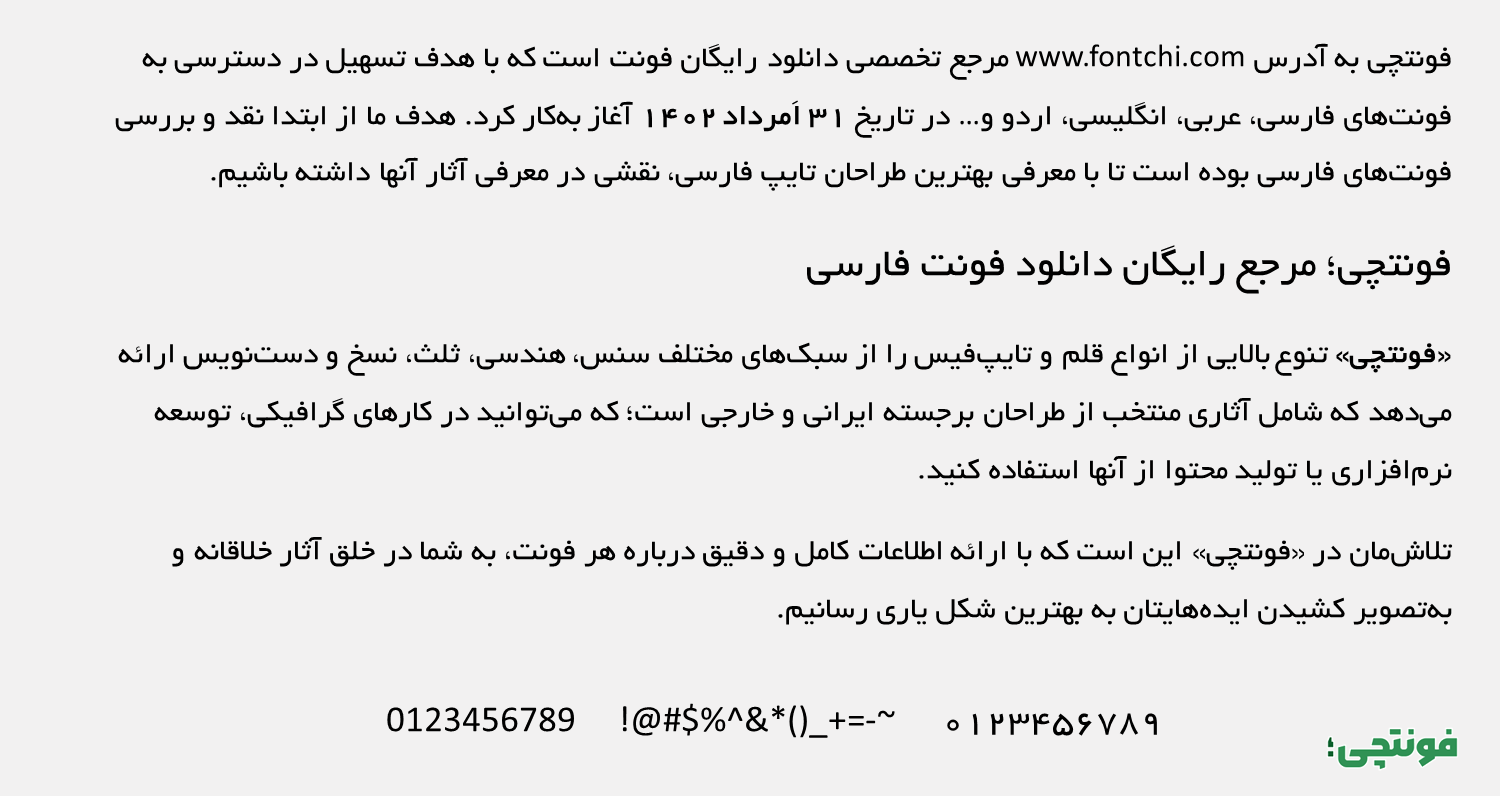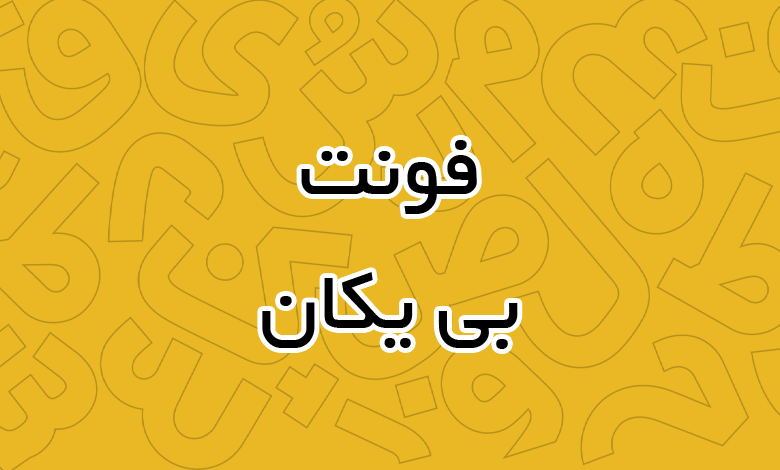
فونت بی یکان (B Yekan)
فونت بی یکان (به انگلیسی: B Yekan) جزو اولین فونتهای فارسی است که بیش از دو دهه از انتشار آن میگذرد. این فونت فارسی دارای یک وزن معمولی است که امکان بولد کردن متون را نیز به شما خواهد داد و بر خلاف سایر فونتهای حرفهای خبری از وزنهای متنوع نیست.
پیشنمایش و امکانات فونت بی یکان (B yekan)
فونت Byekan زمانی ساخته شده است که هنوز استفاده از سیستمهای کامپیوتری خانگی مرسوم نبود. بیشترین سهم استفاده از این فونت را ادارات، سازمانها و پروژههای تحصیلی تشکیل میدادند؛ بهطوریکه حتی در بسیاری کارها، استفاده از این فونت به عنوان یک ضرورت است.
فونت بی یکان به سبک سنس طراحی شده است که دارای ظاهری نرم و در عین حال رسمی است. زوایا و گردیها در این فونت تا حد زیادی خمیده هستند؛ طوری که حروفی مثل «ن، ل، ی» در حالت افقی و عمدی زاویهای نزدیک به ۴۰ درجه را از نقاط تقطیع حروف شامل میشوند که در تصویر زیر پیش نمایش فونت بی یکان را مشاهده میکنید.
نقاط در فونت بی یکان به شکل ناپیوسته و گرد طراحی شده است و مکان قرارگیری نقاط در بالا و زیر حروف کاملا در جای خود قرار دارد. اما به دلیل قدیمی بودن این فونت که در سال ۱۳۷۹ نسخه ۲.۰۱ آن منتشر شده و آپدیتی نیز روی آن اعمال نشده است، ممکن است در برخی ترکیبات کمی ناهماهنگی مشاهده شود. البته زمانی که با اندازه بزرگ تایپ کنید.
فونت B Yekan از محبوبترین سری فونتهای B است؛ از این فونت در موارد متعددی برای انتشارات، چاپ کتاب و مجله، روزنامهها، پروژههای طراحی وب، ساخت تامنیل برای پست شبکههای اجتماعی و ویدئوها و همچنین فونت زیرنویس فیلم و سریال استفاده میشود.
خوانایی این فونت با توجه به سبک طراحی درشتی که دارد برای عموم افراد از سنین پایین تا افراد بزرگسال مناسب است و به خوبی تمامی حروف در آن قابل شناسایی و خواندن است. همین سادگی و در عین حال خوانایی این قلم باعث شده تا فونتهای حرفهای همچون ایران یکان و یکان بخ بر اساس این فونت طراحی شوند.
فونت بی یکان از زبان فارسی پشتیبانی کاملی دارد که میتوانید در زبان عربی نیز حروف و گلیفهایی که مشترک با فارسی هستند را استفاده کنید. اما در این فونت اعداد عربی «۴۵۶» و برخی گلیفهای دیگر این زبان نظیر «ک» وجود ندارد.